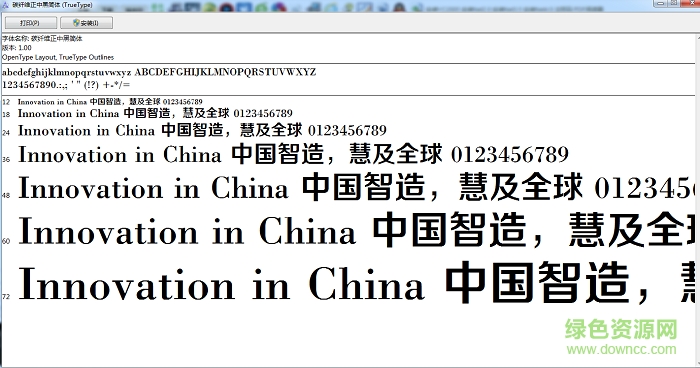
txwzzhongjw gb1 0是什么字體?txwzzhongjw字體就是碳纖維正中黑簡體的英文名稱,字體線條嚴(yán)謹(jǐn)自然,不粗不細(xì),蘊(yùn)含時(shí)代風(fēng)采,需要這款字體的小伙伴快來綠色資源網(wǎng)下載吧!
黑體的各個(gè)筆劃寬度雖是大致相等,但不是絕對(duì)的,在處理上不能強(qiáng)求一律,否則筆劃多的字必然擁塞寫不下,筆劃少的則顯得空,所以應(yīng)在長與短、橫與豎、筆劃粗與細(xì)之間,作適當(dāng)?shù)恼{(diào)整,達(dá)到整體上的均勻諧調(diào)。
字體造型規(guī)整,富于力度,給人以簡潔爽朗的現(xiàn)代感,有較強(qiáng)的視覺沖擊力,這種個(gè)性的字體,適合于機(jī)械科技等主題。